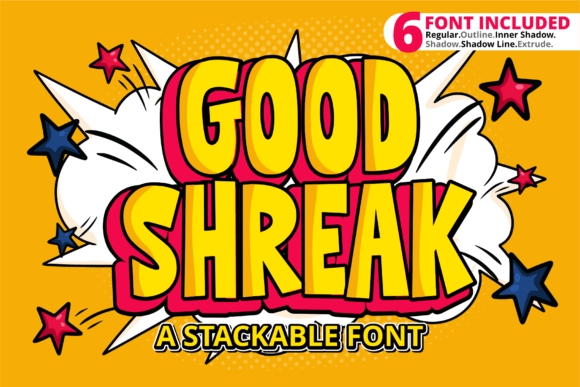
Good Shreak Font
Good Shreak Font – خط عصري وجذاب للمبدعين
أضف لمسة إبداعية وأنيقة إلى تصاميمك مع Good Shreak Font، الخط المثالي للمصممين وصنّاع المحتوى الذين يبحثون عن طابع فريد وأنيق. يتميز هذا الخط بتصميمه العصري والمتوازن، مما يجعله مناسبًا لمجموعة واسعة من الاستخدامات، بما في ذلك:
✔ الشعارات والهويات البصرية
✔ أغلفة الكتب والمجلات
✔ منشورات وسائل التواصل الاجتماعي
✔ التصاميم الإعلانية والترويجية
✔ مشاريع الطباعة والويب